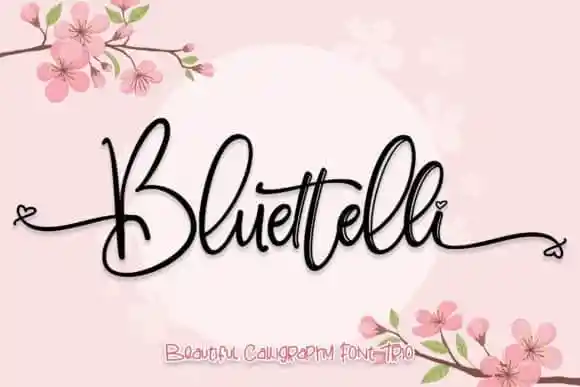
Bluettelli Calligraphy Font – Download Grátis
A Bluettelli Calligraphy Font é uma fonte moderna que combina elementos de três tipos únicos de escrita elegante. Esta trilogia de letras tem diversos caracteres alternativos e ligaturas, criando um conjunto versátil para designers. Ela é ideal tanto para blogs quanto para logotipos, Instagrams, marcas e convites de casamento. As fontes Bluettelli permitem que os designers criem layouts agradáveis e sofisticados em projetos como cartões de visita ou até mesmo em arranjos florais digitais. Seja no design gráfico tradicional ou digital, essa trilogia de letras proporciona o toque final perfeito, dando um toque elegante aos seus projetos sem perder a personalidade única da sua marca.